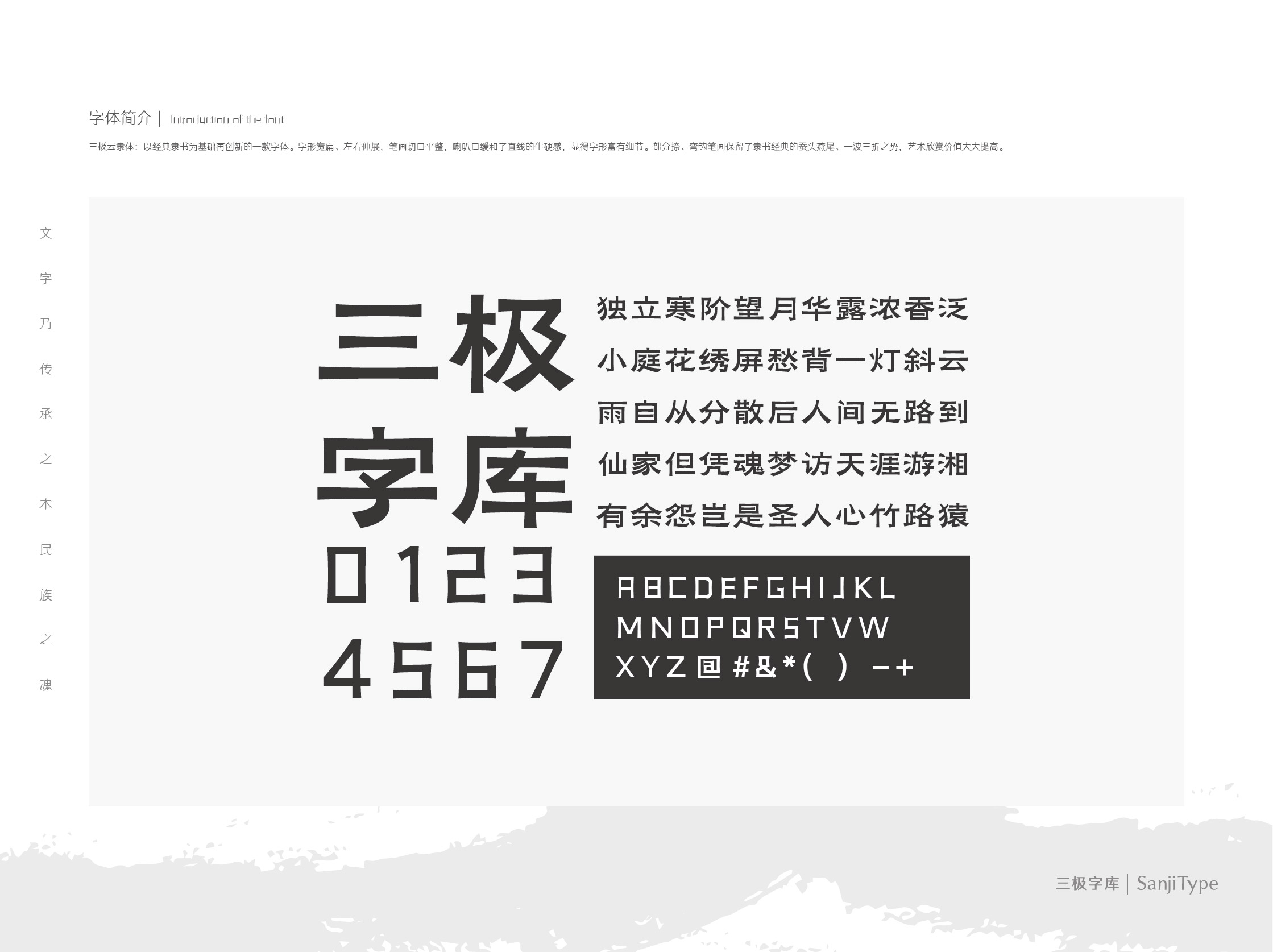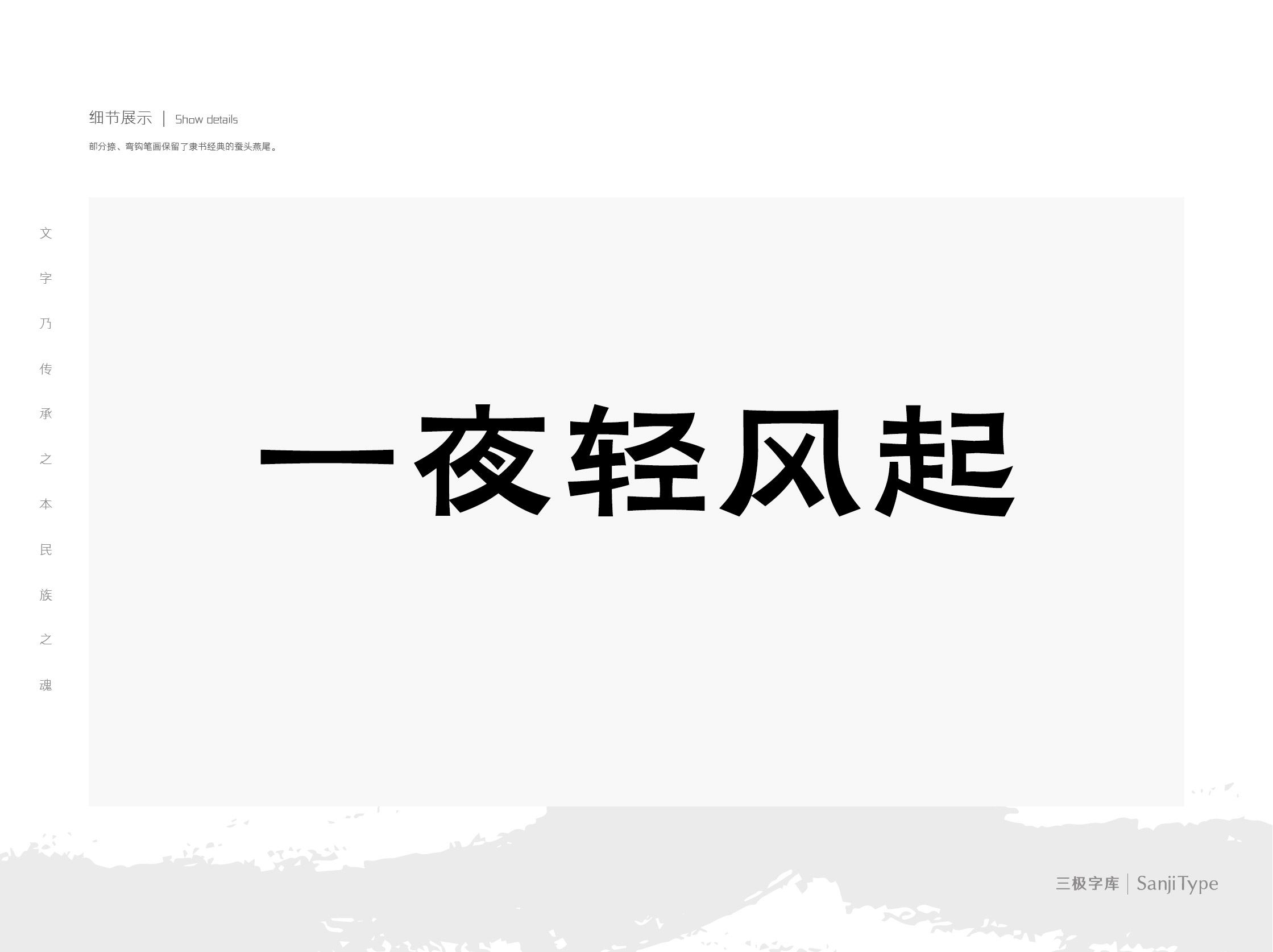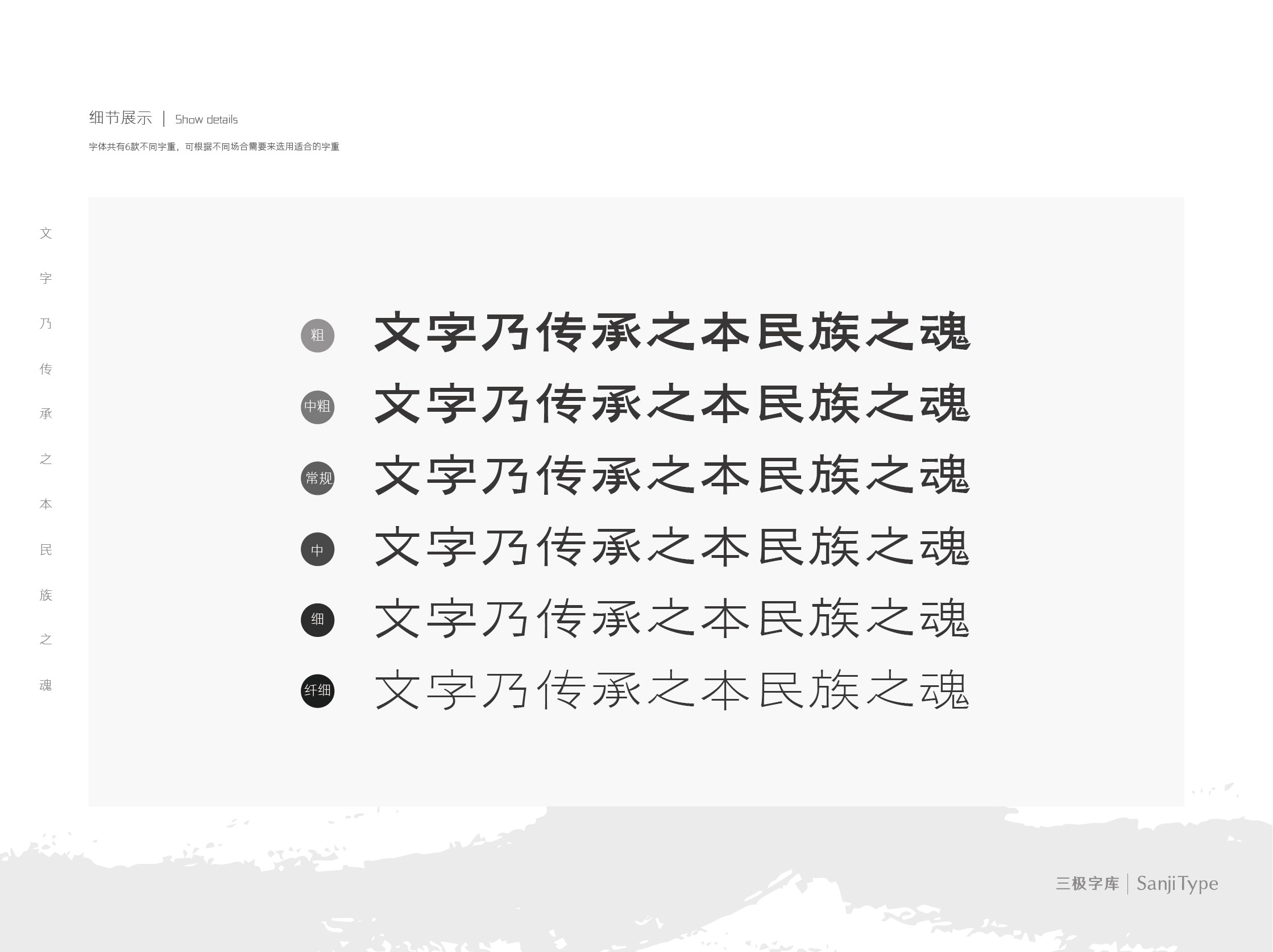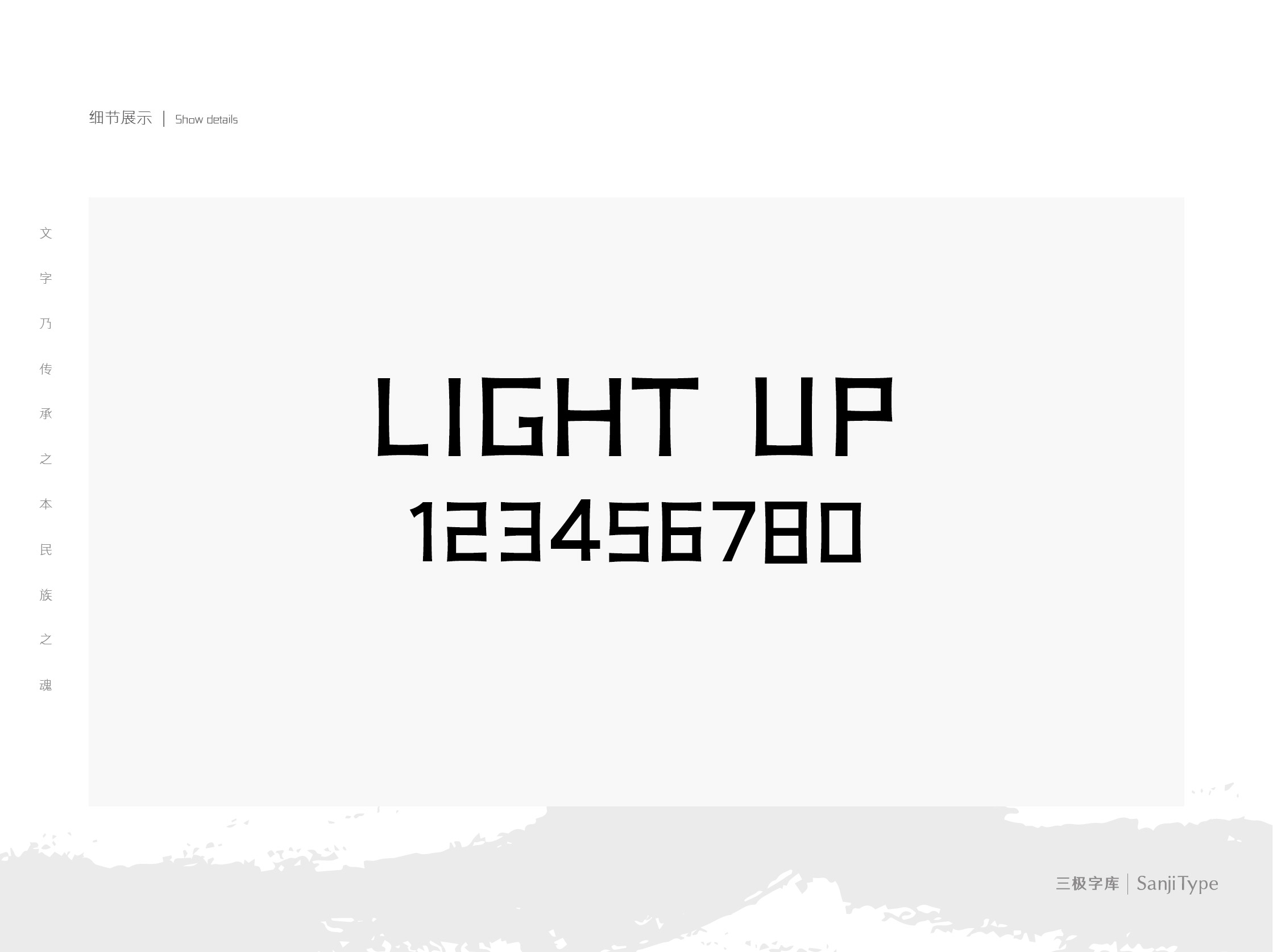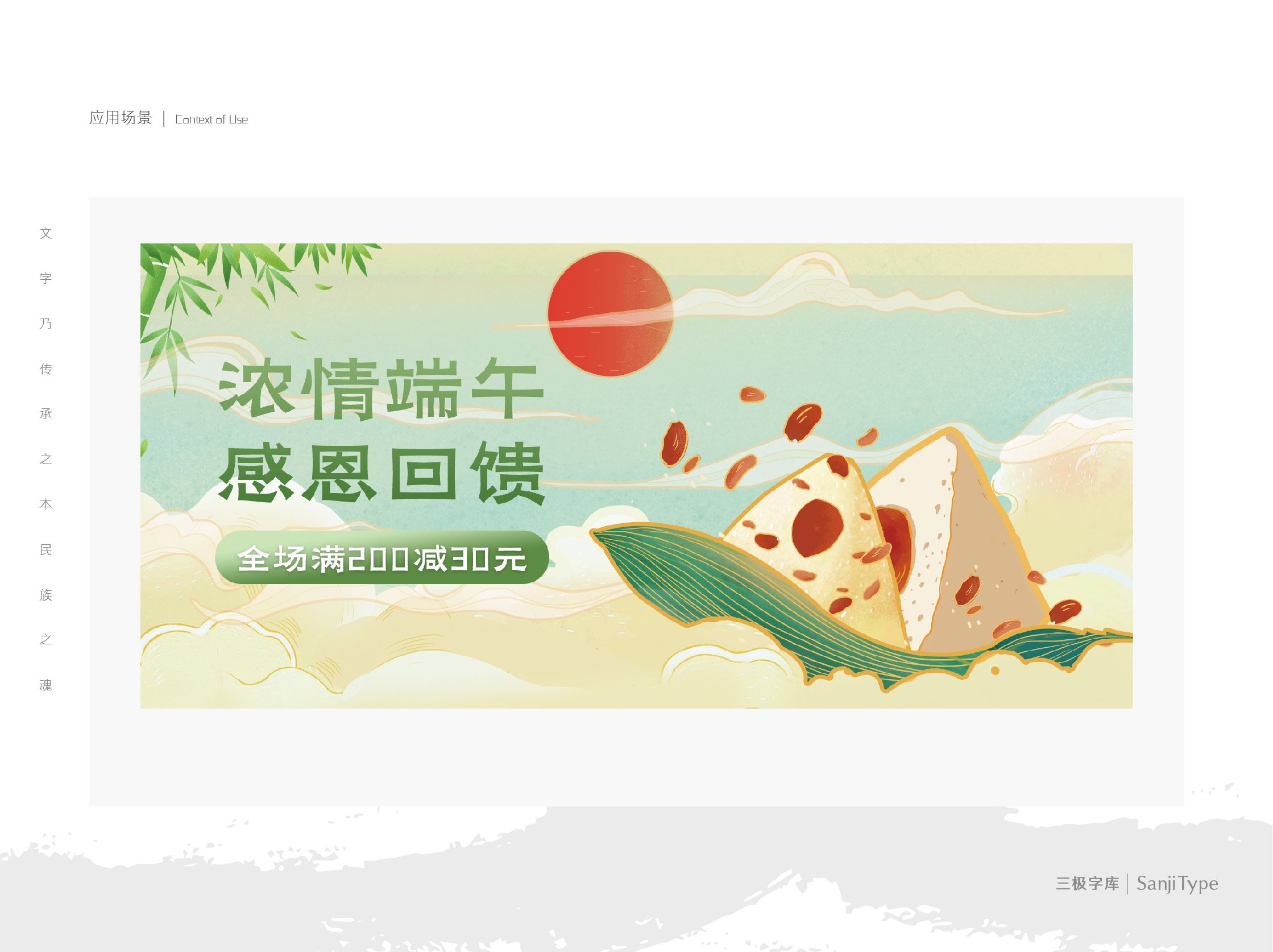
三极云隶体家族
隶书
三极云隶体是以经典隶书为基础再创新的一款字体。字形宽扁、左右伸展,笔画切口平整,喇叭口缓和了直线的生硬感,显得字形富有细节。部分捺、弯钩笔画保留了隶书经典的蚕头燕尾、一波三折之势,艺术欣赏价值大大提高。该字体用于内文中规整又不失活跃感,亦适用于国潮经典、传统节日的主题排版,以及商业类品牌的广告设计。